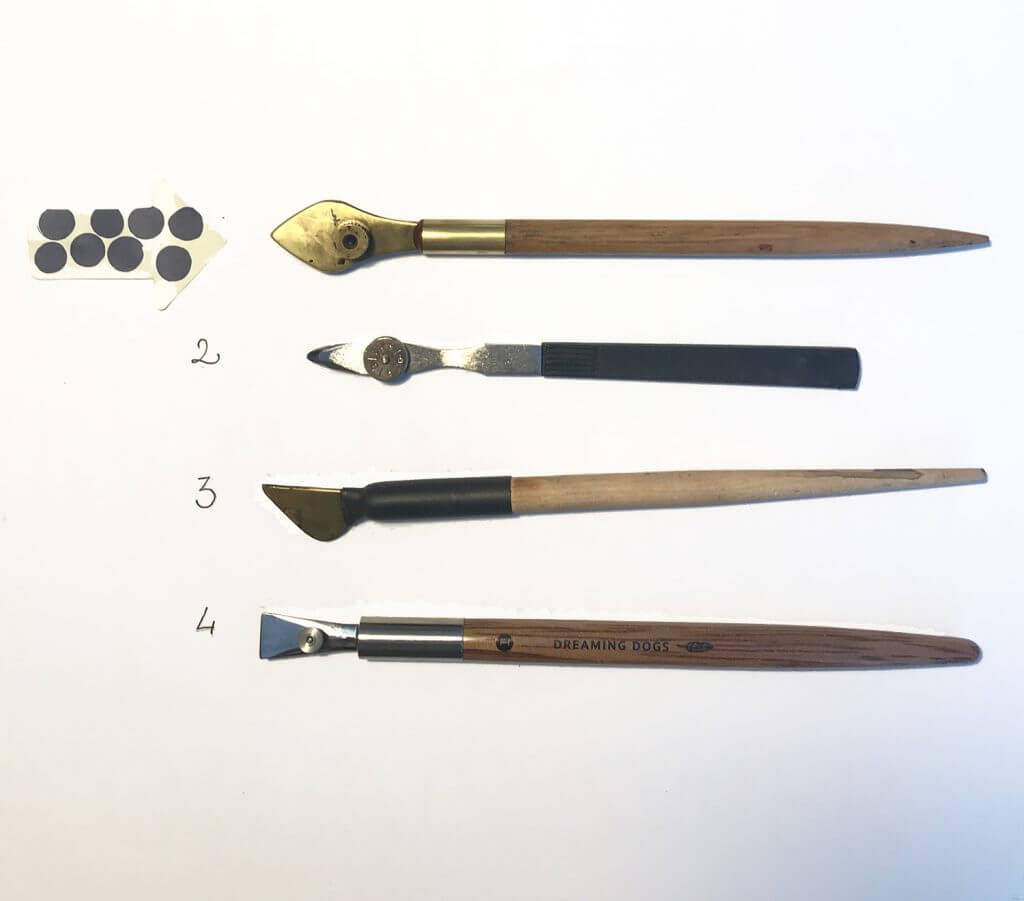
Cette semaine je vais vous présenter outil que j’affectionne particulièrement : le ruling-pen américain. C’est un outil génial et assez aisé pour la prise en main, dédié à la calligraphie gestuelle.
Qu’est-ce qu’un ruling-pen ?
Littéralement, un ruling-pen est un tire-ligne, c’est-à-dire un instrument utilisé à l’origine pour le dessin. On retrouve notamment son utilisation dans le dessin industriel et les plans d’architecte. Le tire-ligne a été dévoyé de sa fonction première par les calligraphes, afin de l’utiliser comme instrument d’écriture.
Il existe différents types de tire-ligne :
• Le tire-ligne américain : celui qui nous intéresse aujourd’hui
• Le tire-ligne suédois, ayant le même principe qu’un tire-ligne d’écolier, mais avec une pointe plus large qui retient davantage d’encre (2)
• Le cola-pen : instrument inspiré du tire-ligne créé par des calligraphes (3)
• Tire-ligne carré : pour explorer d’autres styles, notamment la gothique (4)
Anatomie du ruling-pen américain
Le ruling-pen  américain  a été mis au point à la fin du XXe siècle pour la calligraphie. Il possède 2 lames en laiton, qui sont reliées par une vis (virole). Le réglage de la vis permet de serrer ou desserrer l’écartement des lames et d’obtenir un trait plus ou moins gras en réglant le débit d’encre.
La forme même des lames permet également de jouer sur la graisse du trait : soit on écrit avec la pointe, un trait fin plus ou moins épais. Soit on utilise la tranche de la lame : pour un trait épais.
Utilisation de la pointe pour un trait fin
Utilisation de la tranche pour un trait gras
Prise en main du ruling-pen américain, chargement et entretien
Le ruling-pen se tient comme un stylo. Le manche en bois est d’ailleurs très ergonomique et agréable en tenue. L’encre est chargée en trempant la pointe directement dans le flacon. La pointe doit être généreusement chargée. La gestuelle est gourmande en encre !
Comme pour les plumes métalliques, un petit nettoyage à l’eau et au savon est nécessaire pour retirer la pellicule protectrice sur les lames neuves. Si l’encre ne semble pas bien adhérer aux lames, un peu de salive fera l’affaire pour une parfaite accroche (sur plume propre évidemment, inutile de se barbouiller avec une plume pleine d’encre !)
Quels médiums utiliser ?
Il faut un médium très fluide, bien sûr, donc une encre liquide de type Ecoline, Colorex, Gallo-ferrique, brou de noix… Attention aux encres acryliques et à l’encre de chine, qui encrassent les lames. Vous pouvez les utiliser, mais il faudra bien rincer votre instrument immédiatement après usage. Ce sont les mêmes recommandations que pour les plumes métalliques. Il faut en prendre grand soin, d’autant que c’est un outil assez cher.
Quel support utiliser ?
Comme l’écriture se fait avec un médium très fluide, je vous conseille un papier assez épais (120g minimum).
Les premiers traits
La prise en main du tire-ligne américain passe par la réalisation de traits. C’est la base de la calligraphie gestuelle.  On oublie les lettres, on pense « trait ».
Le geste doit être vif, vigoureux, mais réfléchi (on ne fait pas du gribouillage). Pour s’exercer, rien de tel qu’une grande feuille A3 ou encore A2, un bureau bien dégagé qui ne gêne pas les mouvements, un gros pot d’encre, éventuellement un tablier pour se protéger des projections d’encre. Pour les traits ci-dessous, garder les lames assez écartées, pour une bonne fluidité.
Pour démarrer, s’exercer à faire des traits
La lame est toujours perpendiculaire au trait : il faut donc tourner votre poignet constamment
Les premières lettres
Essayez de faire des capitales simples, en prenant soin de bien tourner votre poignet pour conserver la lame perpendiculaire au trait.
Comment faire pour que ça crache ? Pour obtenir un effet de trace qui « crache », il faut que le tire-ligne soit bien chargé et les lames suffisamment écartées. Après, ça ne se calcule pas tellement : c’est la vigueur du geste qui va provoquer ou non des éclaboussures.
Pangramme avec un mot manquant ! désolée..
Comme toujours, avec un peu d’entrainement, vous vous habituerez à ce nouvel outil, et j’espère que cela vous donnera envie d’explorer davantage la calligraphie contemporaine.